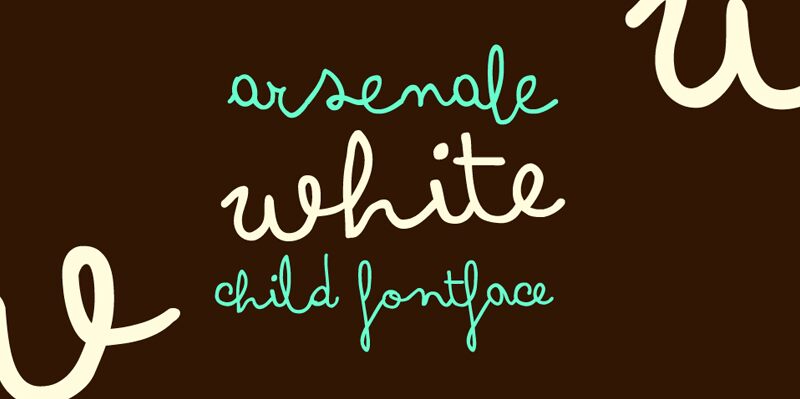
Arsenale White, zaprojektowany przez Francesco Canovaro, Jonathana Calugiego i Studio Kmzero, to darmowy krój pisma typu monoline script o szybkim zamachu osobistego podpisu. Jego połączone litery przepływają przez szerokie pętle i ostre zakręty, a nieregularna linia bazowa nadaje pismu luźny i spontaniczny charakter.
Naturalnie sprawdza się na etykietach modowych i okładkach albumów, gdzie długie pociągnięcia mogą posłużyć jako mocny akcent graficzny. Zaproszenia i papeteria osobista również pasują do jego swobodnego, odręcznego stylu. Ciągła linia zyskuje dzięki dużej ilości wolnej przestrzeni, dzięki czemu jej pętle i skrzyżowania pozostają czytelne.